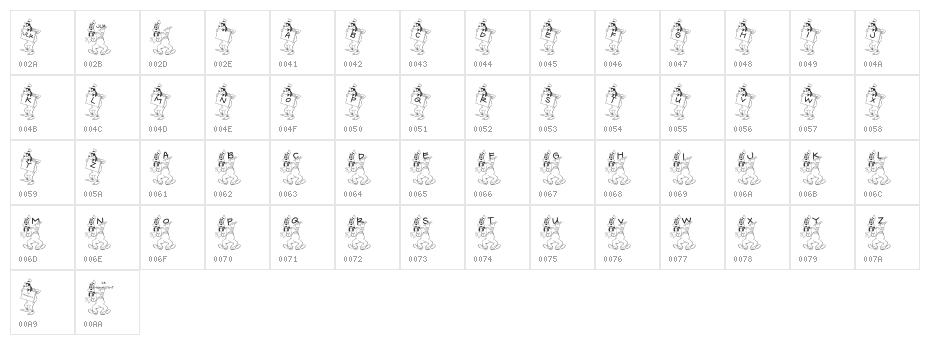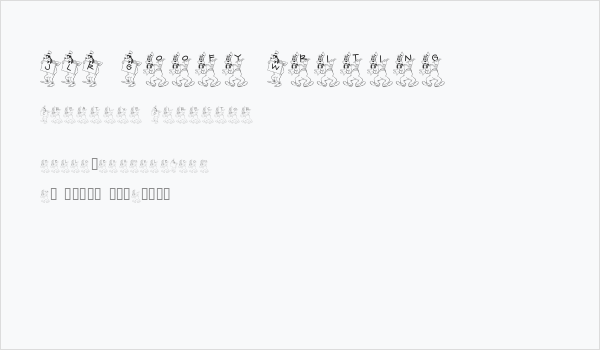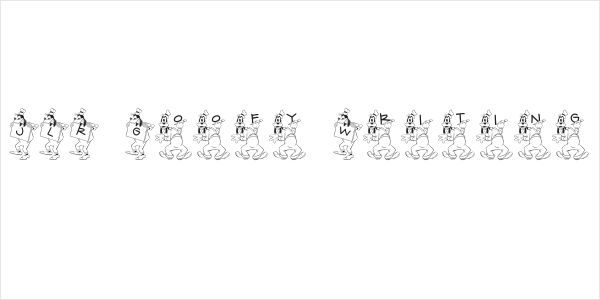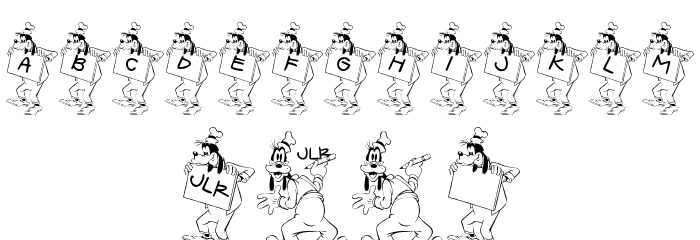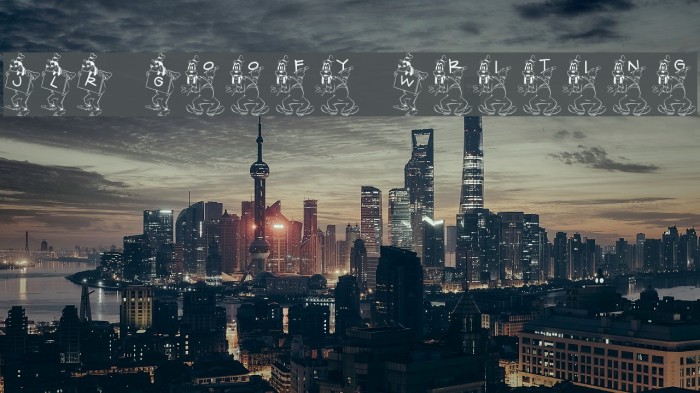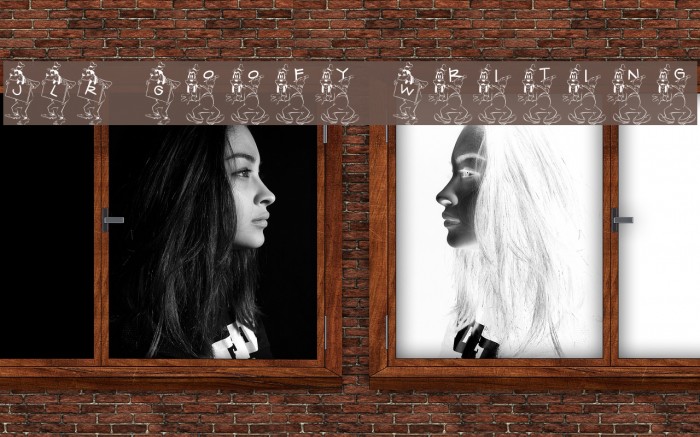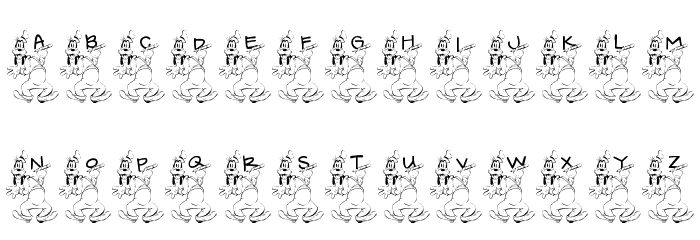
JLR Goofy Writing Font
| समग्र शैली | Whimsical, Fun |
| उपयोग का मामला | Logos, Posters, Invitations |
| सुझाए गए प्रोजेक्ट | Ideal for children's books, playful branding, party invitations, and themed event materials. |